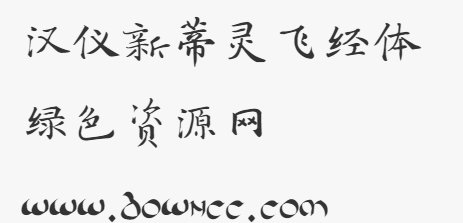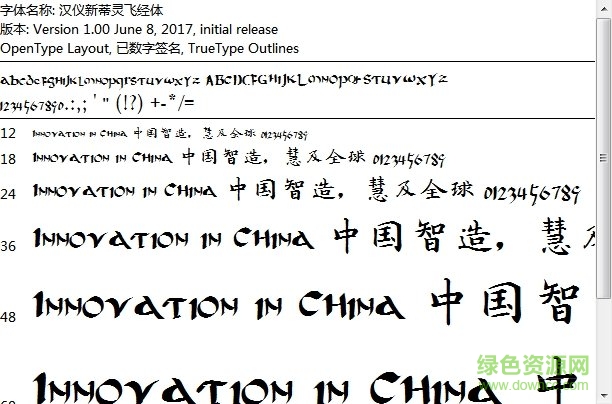
漢儀新蒂靈飛經(jīng)體是漢儀字庫和新蒂聯(lián)合推出的一款古風(fēng)字體,以楷書為模板,字跡娟秀得體,更顯飄動(dòng)靈敏之氣,整體效果十分出色,喜歡的朋友就來綠色資源網(wǎng)免費(fèi)嘗試吧!
新蒂2018年主打字體,以唐小楷《靈飛經(jīng)》為藍(lán)本復(fù)刻。兼容繁簡,有獨(dú)立制作的西文。風(fēng)格統(tǒng)一,擴(kuò)展字形完美融合。
靈飛經(jīng)是道教經(jīng)名,主要闡述存思之法。今道藏有《上清瓊宮靈飛六甲左右上符》,一卷?!稘h武內(nèi)傳》謂此經(jīng)用于請(qǐng)命延算、長生久視、驅(qū)策眾靈、役使鬼神。 《靈飛經(jīng)》是唐代著名小楷之一,無名款。元袁桷,明董其昌皆以為唐鐘紹京書,但啟功先生認(rèn)為只是無名經(jīng)生所書。鐘紹京,字可大,虔州贛人。官至中書令,越國公。書學(xué)二王、褚、薛,在當(dāng)時(shí)是享有盛名的書家,時(shí)號(hào)“小鐘”,也是收藏家,個(gè)人收藏名家真跡數(shù)百卷?!鹅`飛經(jīng)》筆勢圓勁,字體精妙。后人初習(xí)小楷多以此為范本。